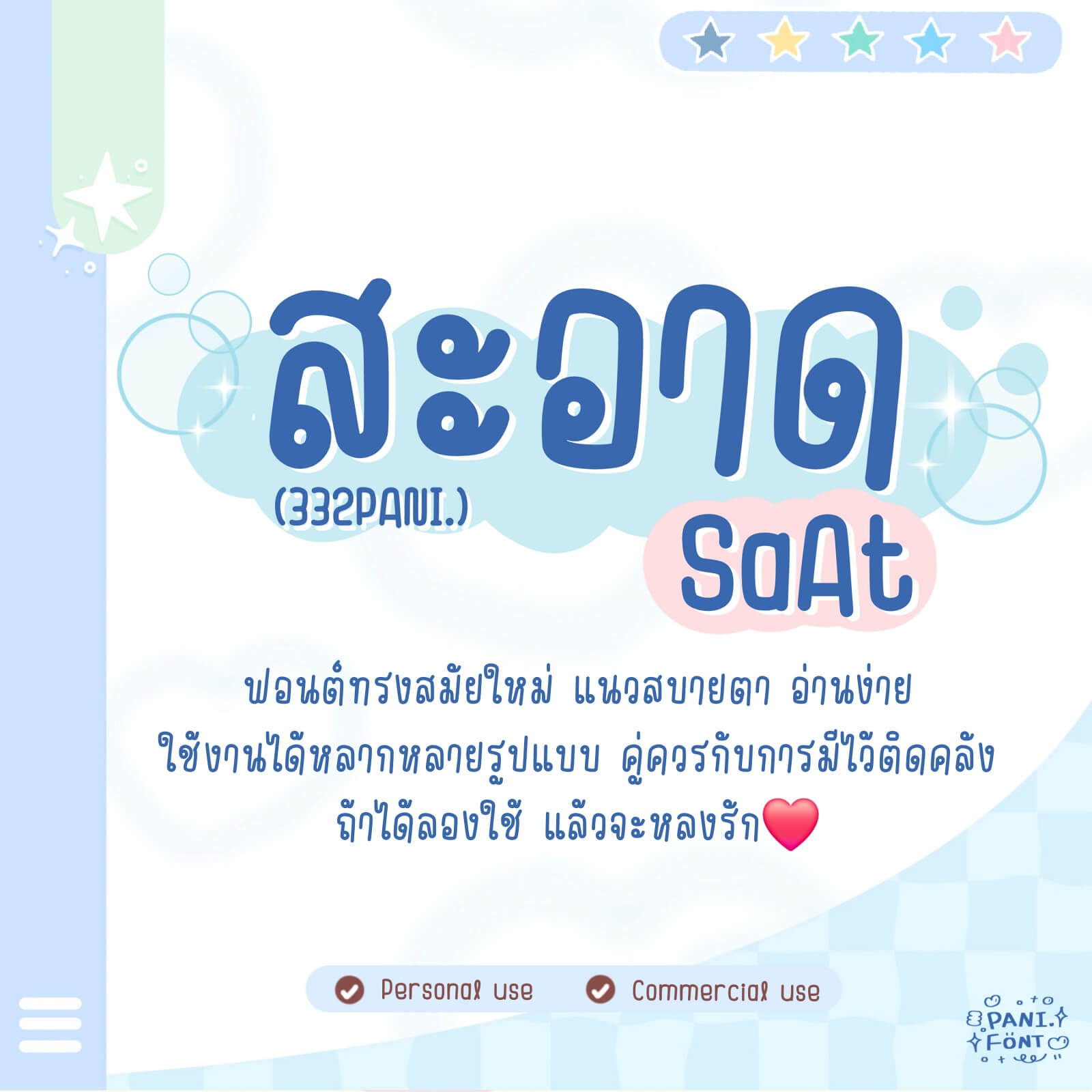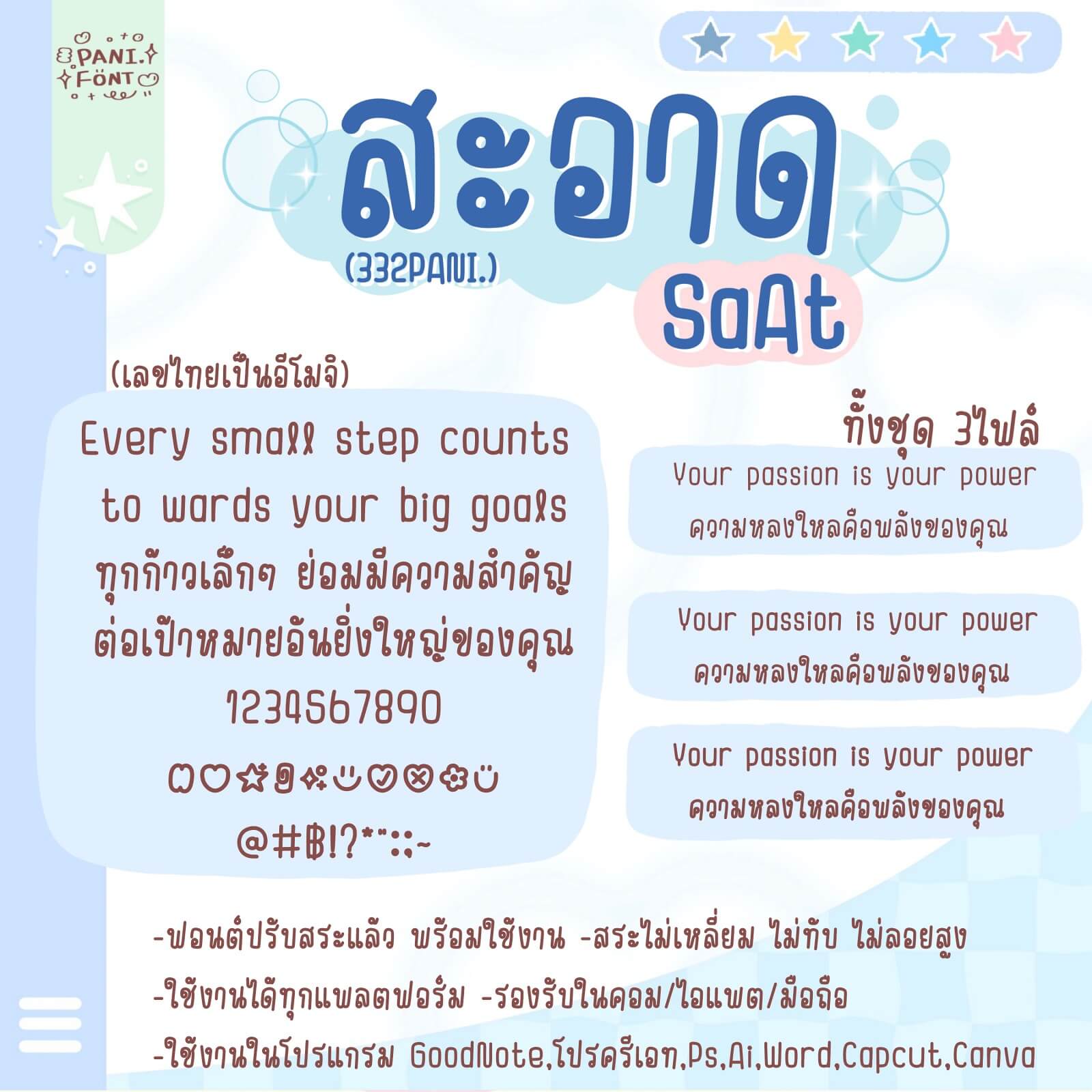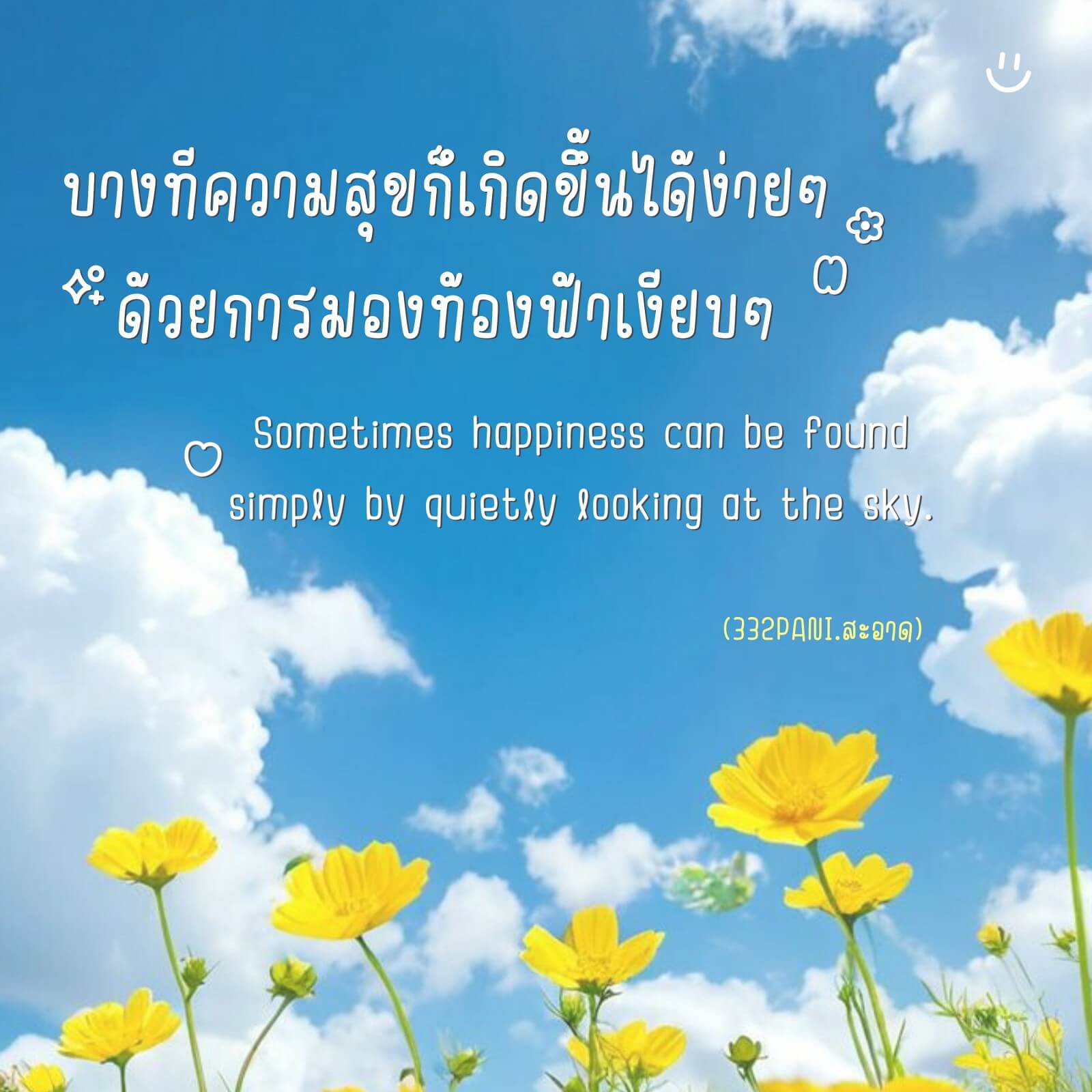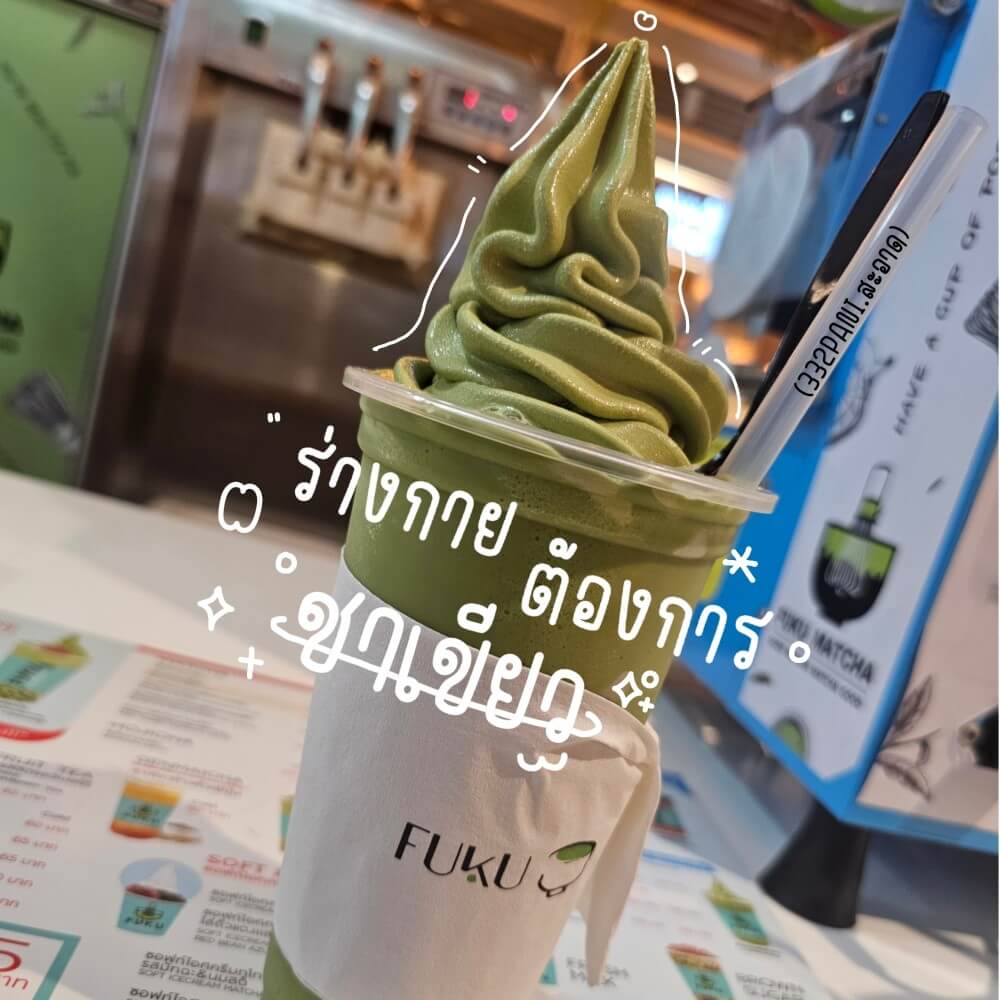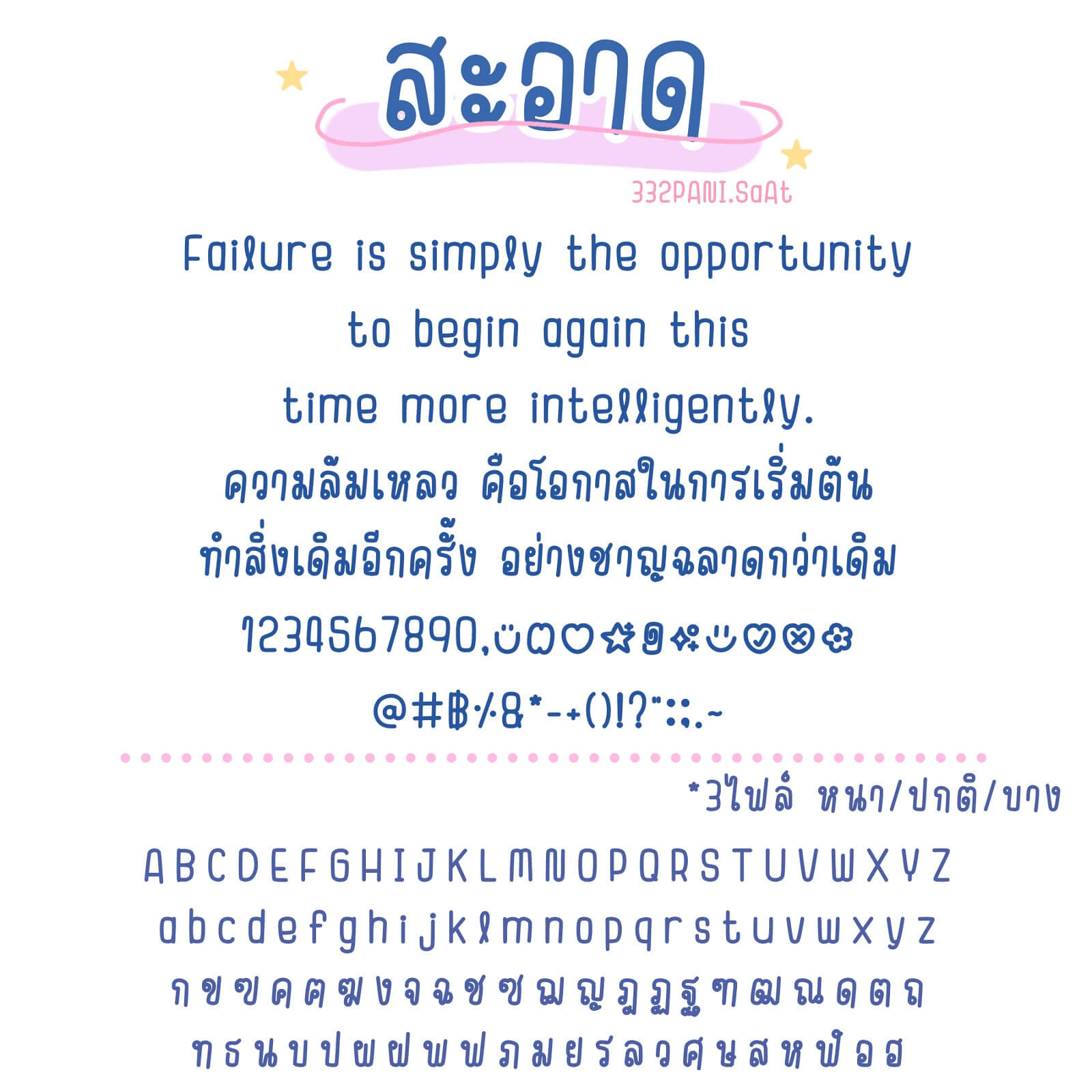
ฟอนต์ 332PANI.สะอาด – โหลดทดลองใช้ฟรีตัว Demo ฟอนต์ทรงสมัยใหม่ แนวสบายตา อ่านง่าย ใช้งานได้หลากหลายรูปแบบ คู่ควรกับการมีไว้ติดคลัง ถ้าได้ลองใช้ แล้วจะหลงรัก
332PANI.สะอาด